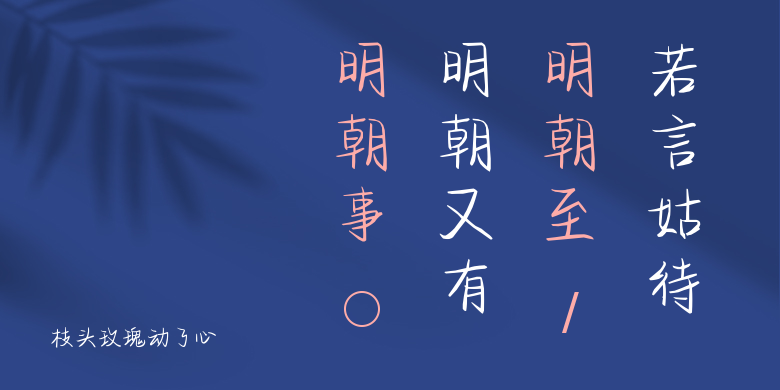
枝头玫瑰动了心
枝头玫瑰动了心,这款字体结构工整、笔画清晰,兼顾美观与易读性,适用于标题、正文、海报、包装、LOGO 等多种场景。字形优雅稳定,风格百搭耐看,适配日常排版与创意设计,让文字呈现更舒适、更具质感。枝头玫瑰动了心一笔一画,皆是细节,以均衡的比例、流畅的线条打造舒适视觉体验,字形端正大气,风格简约现代。无论是商业设计、品牌宣传还是日常排版,都能轻松驾驭,让文字更有格调与力量。枝头玫瑰动了心字体下载。